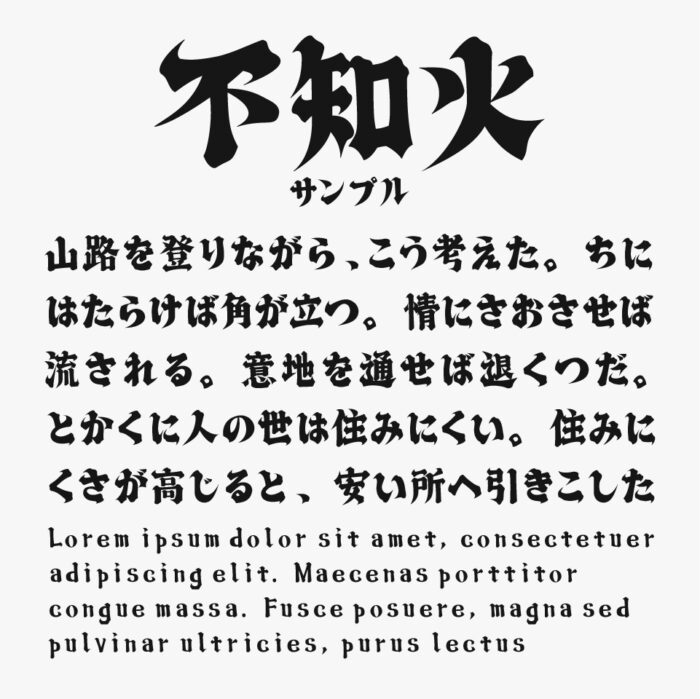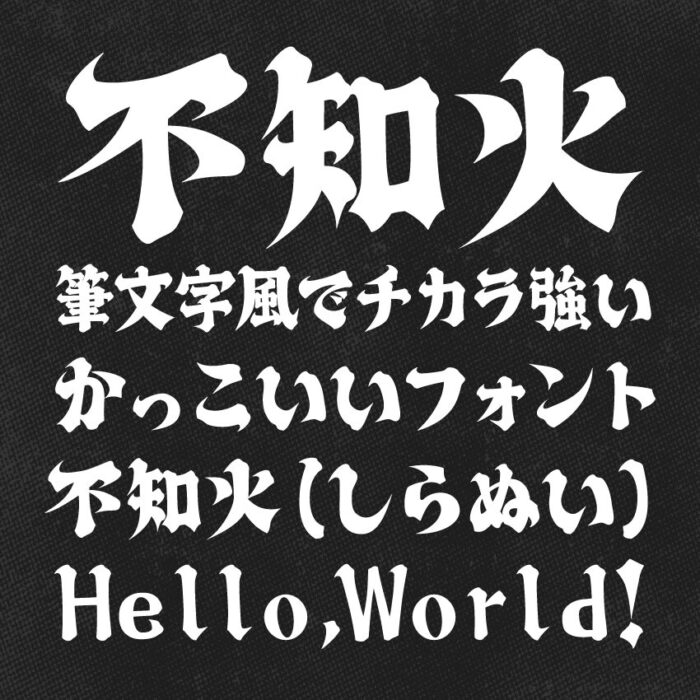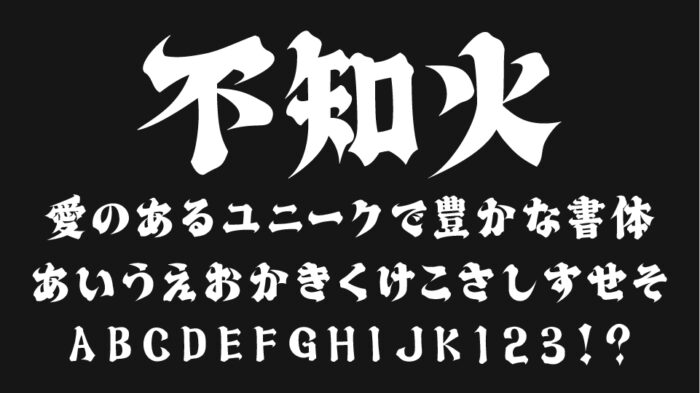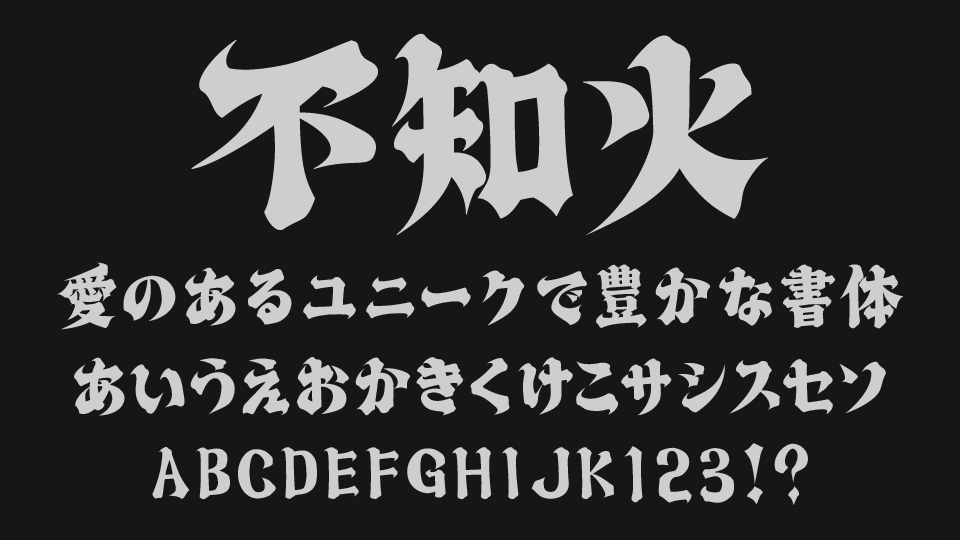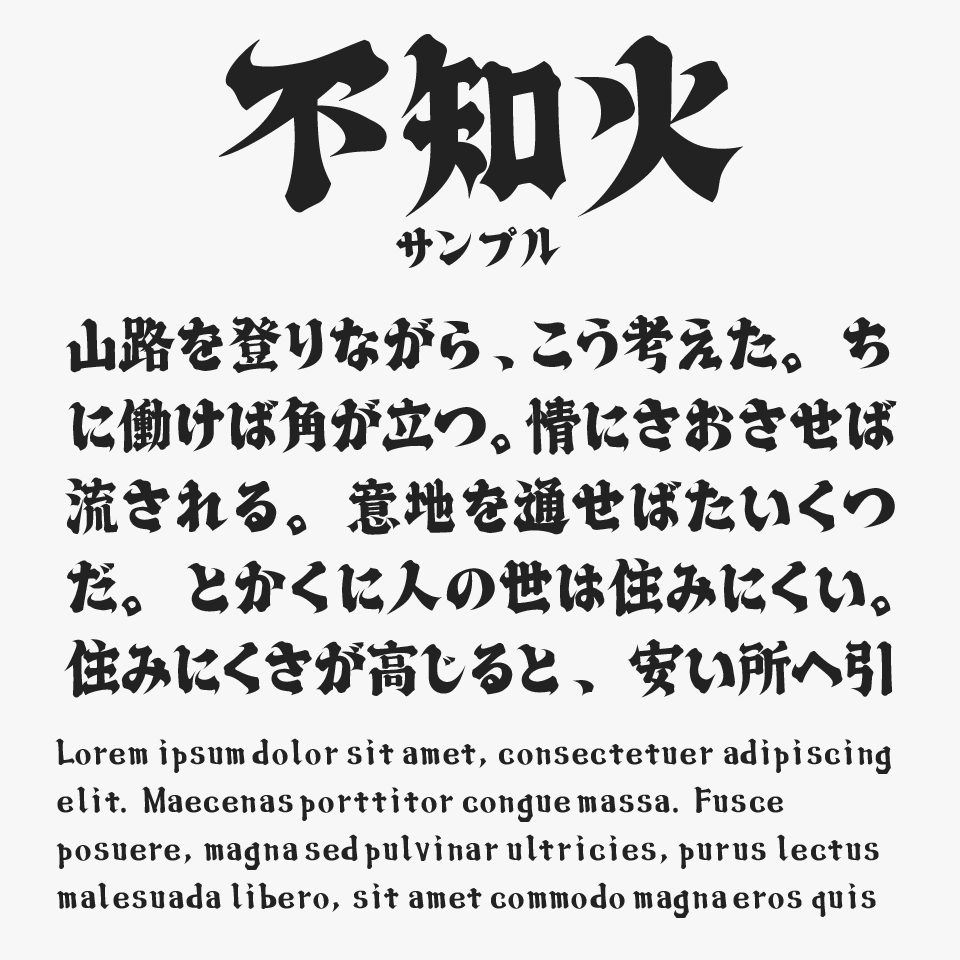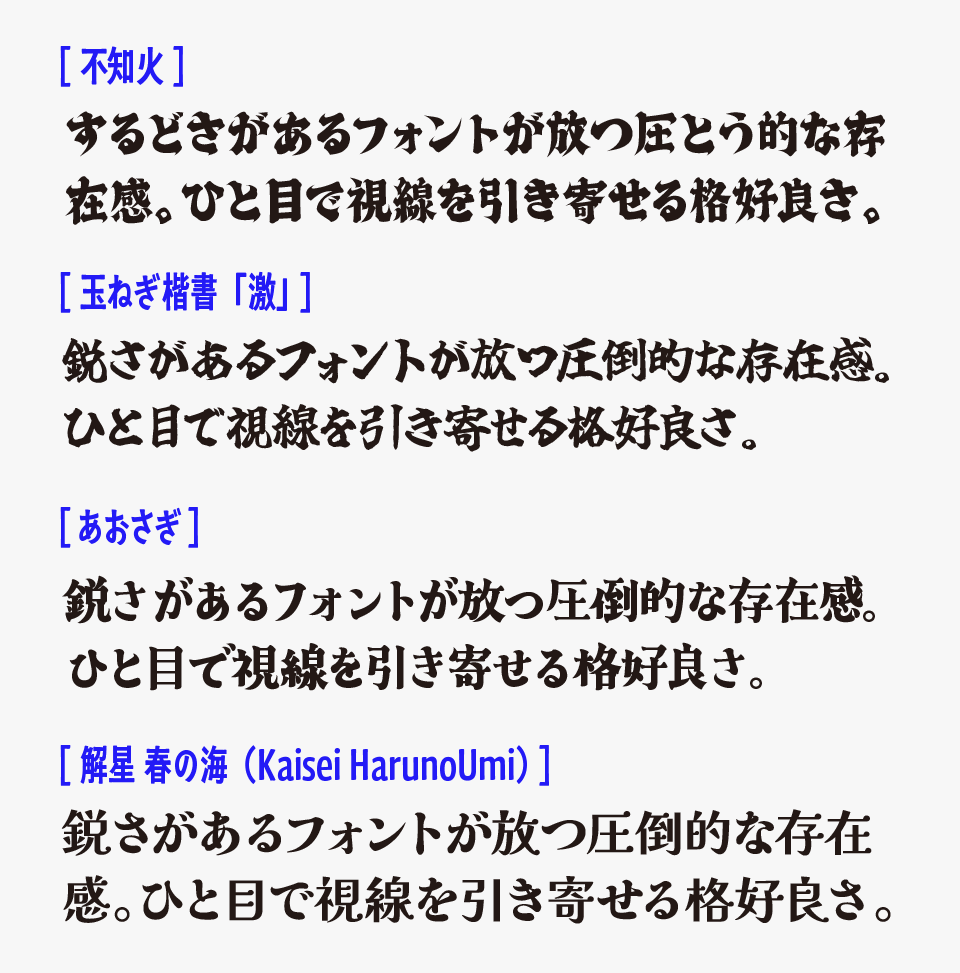
不知火(しらぬい)フォントは、荒々しい筆致が特徴的な力強さを感じる筆文字風フォントです。
エッジの立った鋭い筆画と、墨のにじみを思わせる揺らぎが絶妙に融合しており、書道のような筆文字を漂わせる力強いフォントです。重厚な造形と、ひらがな・カタカナの抑揚のあるフォルムが、迫力と古風な雰囲気のあるデザインです。
力強く威厳あるデザインなので、タイトルロゴや見出し用途、和風ホラー、妖怪、剣劇、戦国などの世界観を表現するのにぴったりなフォントです。